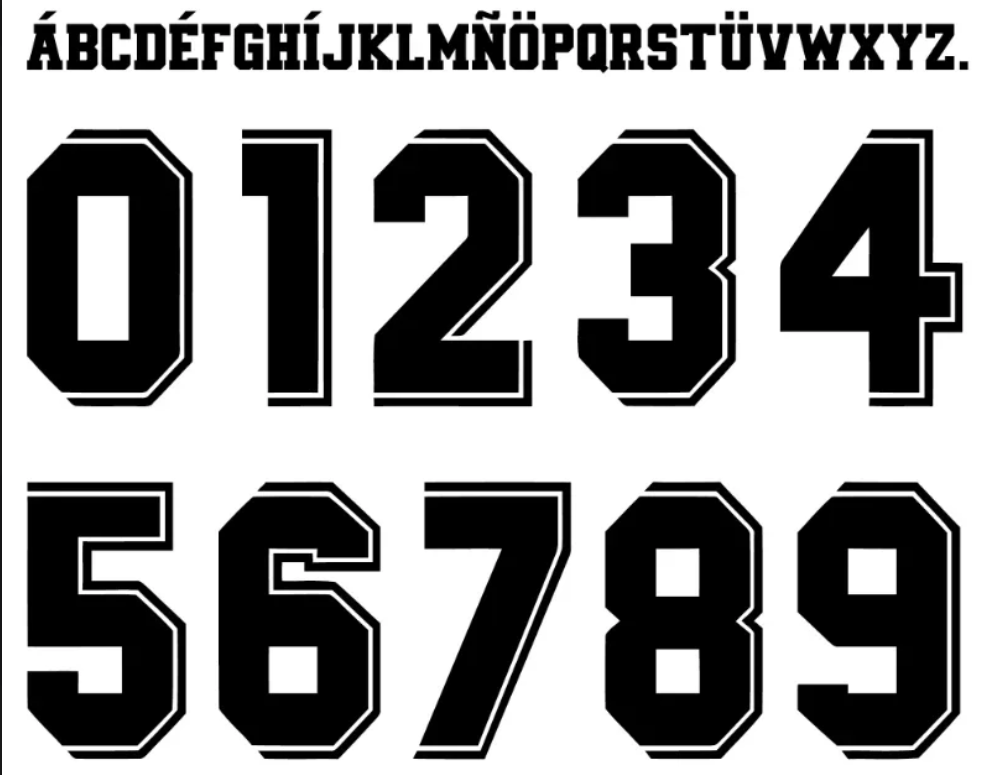
Se existe uma época dourada que faz o coração de qualquer corinthiano bater mais forte, é o início da década de 90. Estamos falando da era do Craque Neto, da raça inigualável e, claro, da conquista histórica do primeiro Campeonato Brasileiro em 1990.
Para celebrar esse momento icônico, trazemos para download a Fonte Corinthians 1990-1994. Esta é a tipografia exata utilizada nas camisas fabricadas pela lendária Finta, que vestiram o Timão durante uma de suas fases mais vitoriosas. Se você trabalha com personalização de camisas, design esportivo ou quer restaurar um manto sagrado, este arquivo é essencial na sua coleção.
O Estilo Visual: A Marca da Raça
A tipografia utilizada pelo Corinthians entre 1990 e 1994 reflete a estética robusta do futebol daquela época. Diferente das fontes modernas e minimalistas da Nike atual, os números desta era possuem um design:
- Blocado e Serifa Grossa: Transmite solidez e peso, características que combinavam com o estilo de jogo aguerrido do time.
- Numeração 3D (Variação): Em algumas versões da camisa, especialmente a listrada, os números apresentavam um sombreamento clássico que dava profundidade à estampa.
- Legibilidade Máxima: Desenhada para ser vista de longe nos estádios lotados, seja no Pacaembu ou no Morumbi.
É a fonte perfeita para recriar a mítica camisa 10 do Neto ou a 8 do Wilson Mano.